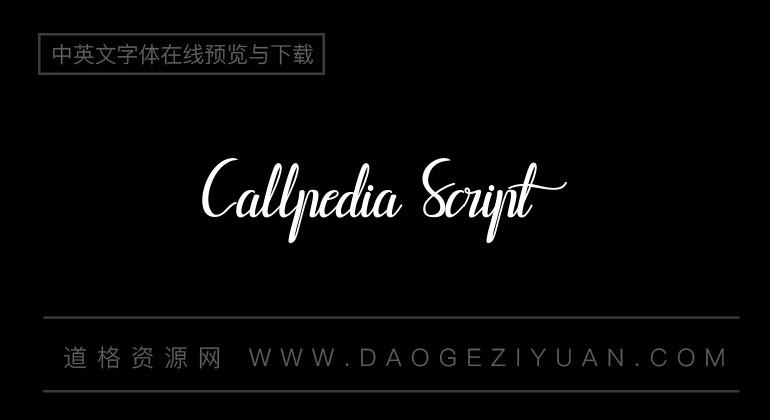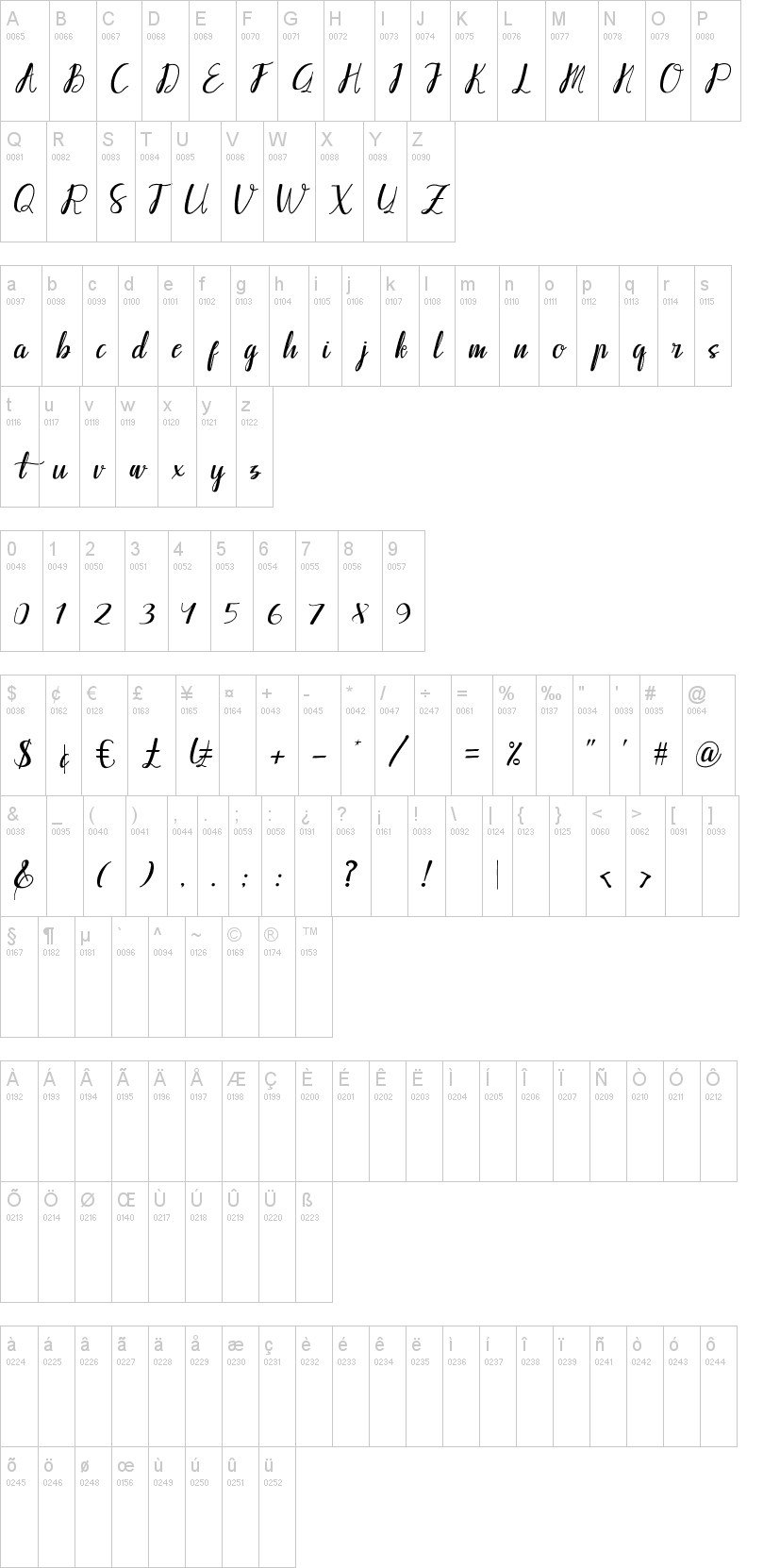
Callpedia Script
Callpedia Script 是一款具有时尚感的脚本字体,它的特点是字体的线条比较细,比较优雅,字体的样式比较新颖,而且字体的结构也比较精致,比较细腻,可以用于各种设计项目中,比如海报、婚礼邀请卡、书籍封面等等。
Callpedia Script是一款非常不错的手写艺术字体,具有很好的视觉感,适合于文化类的宣传设计、商业类品牌的广告和产品包装设计以及个性化文字排版等较多场景。